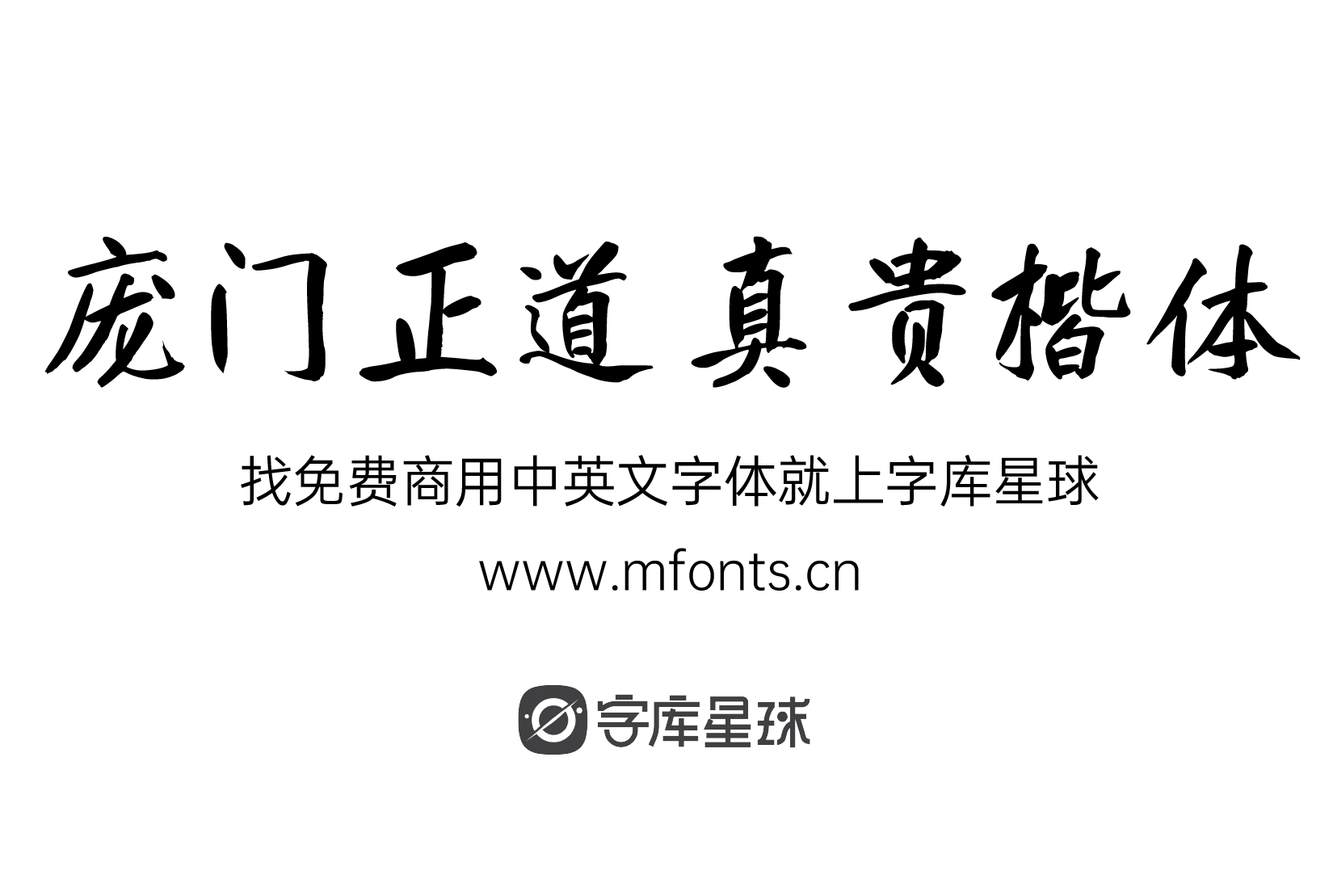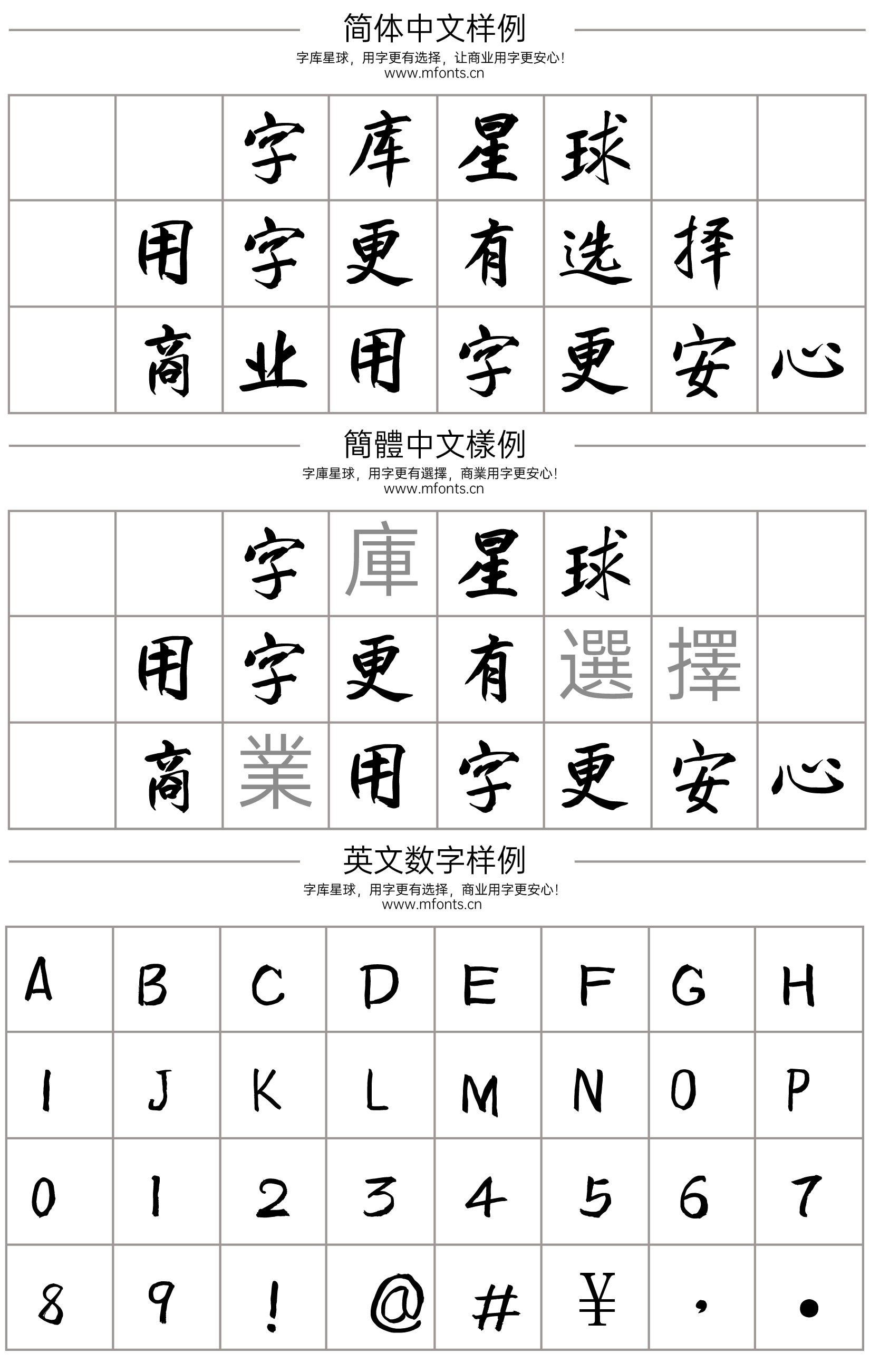
庞门正道真贵楷体
庞门正道真贵楷体由庞门正道的父亲庞真贵老先生,于76岁高龄历时9个月书写制作而成,中间经过了复杂且繁琐的重写、修改、完善等,使得字体效果更适合商业使用。庞门正道真贵楷体
该字体已覆盖常用的中文简体汉字(约6600个汉字),简体基本不存在缺字的现象,繁体则支持较少,但是已经非常可以满足基本的用字。庞门正道真贵楷体
庞门正道真贵楷体保留了毛笔书写过程中留下的手写痕迹,在起笔、收笔、转折处会有明显的毛笔的痕迹,这使得字体更加接近手写的自然,有一种天然的质朴感。庞门正道真贵楷体
字体的粗细使用,用力也非常均匀,字体笔画的粗细基本保持一致,即便是大面积使用也非常适于阅读。 庞门正道真贵楷体